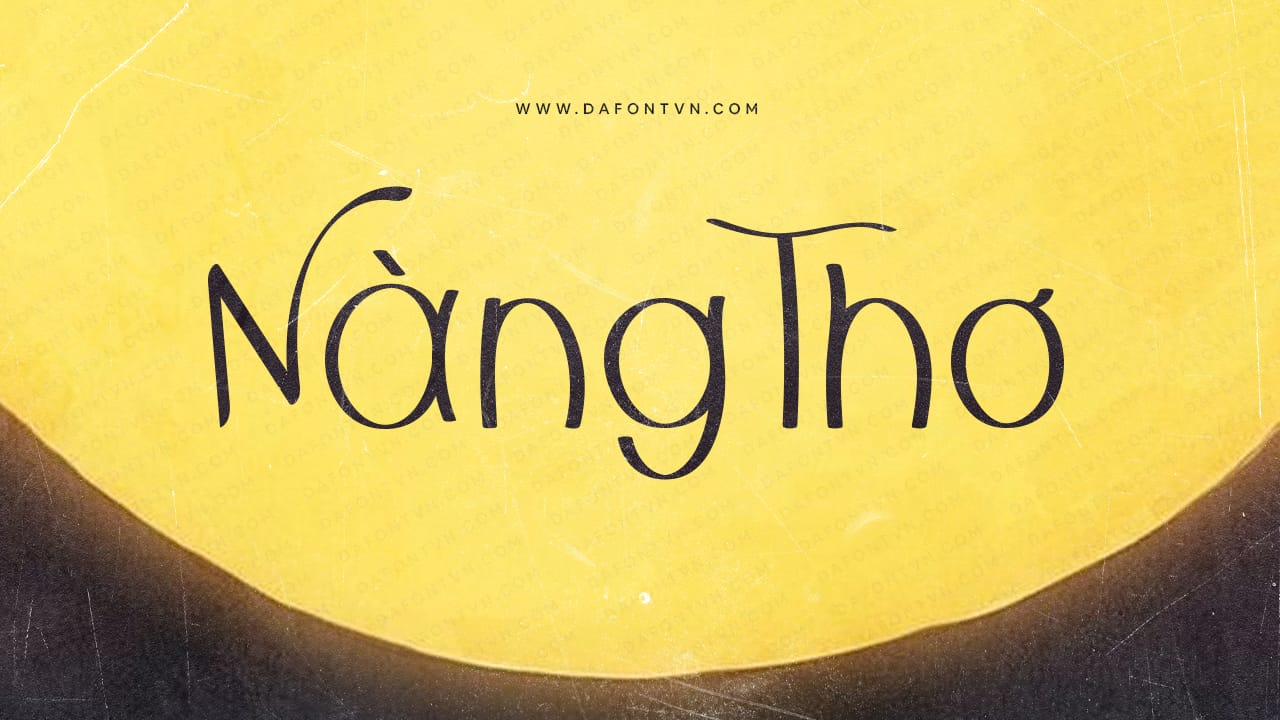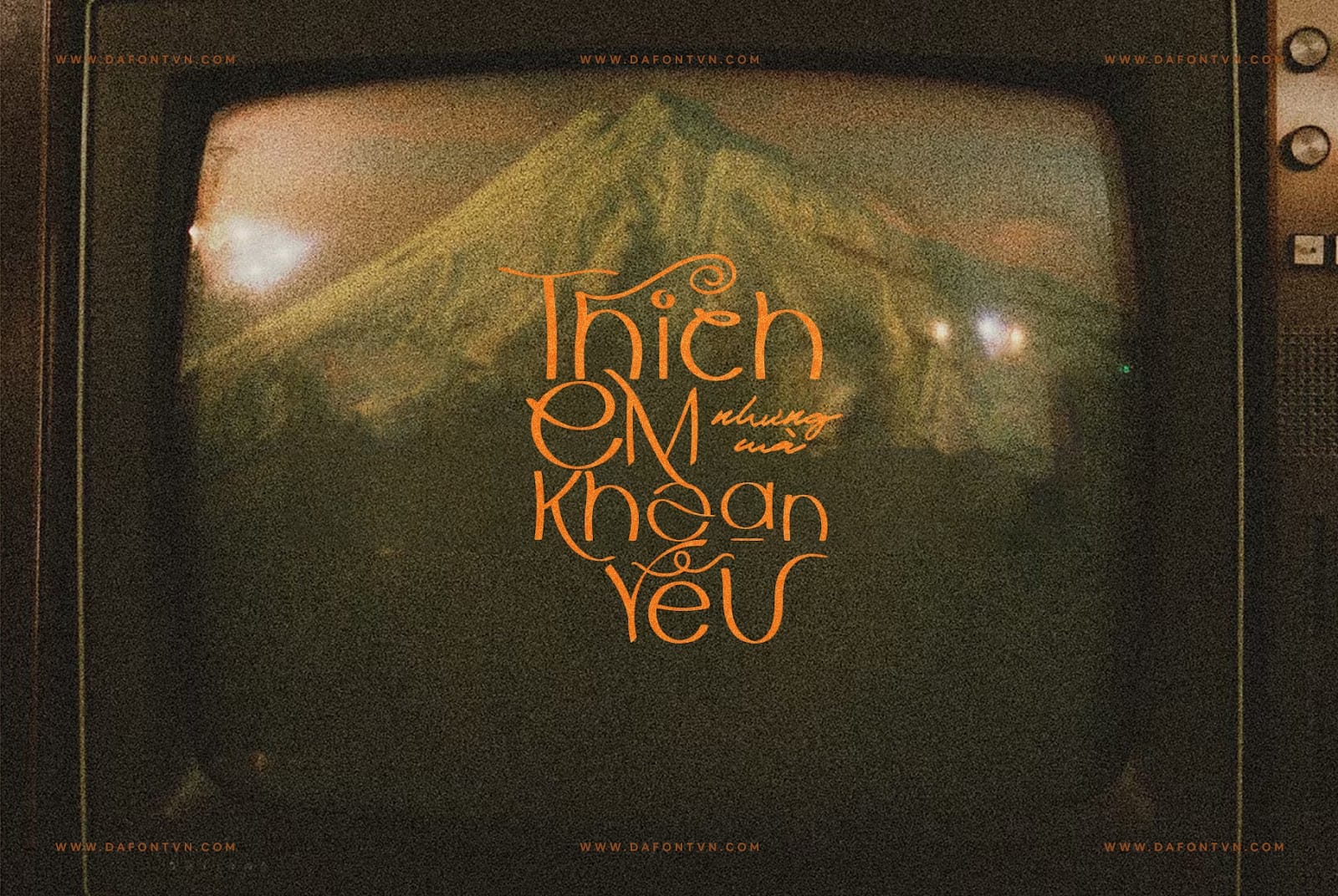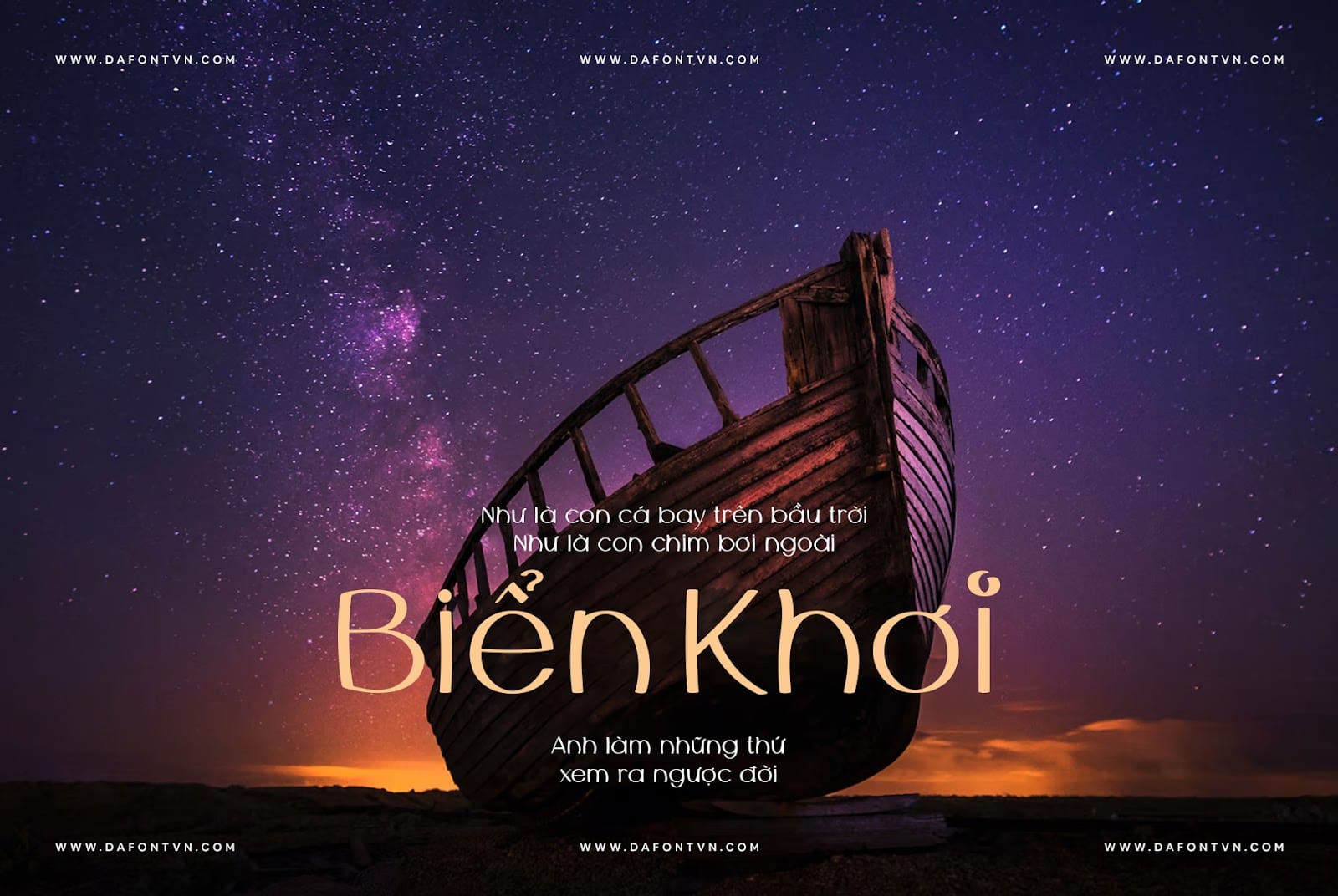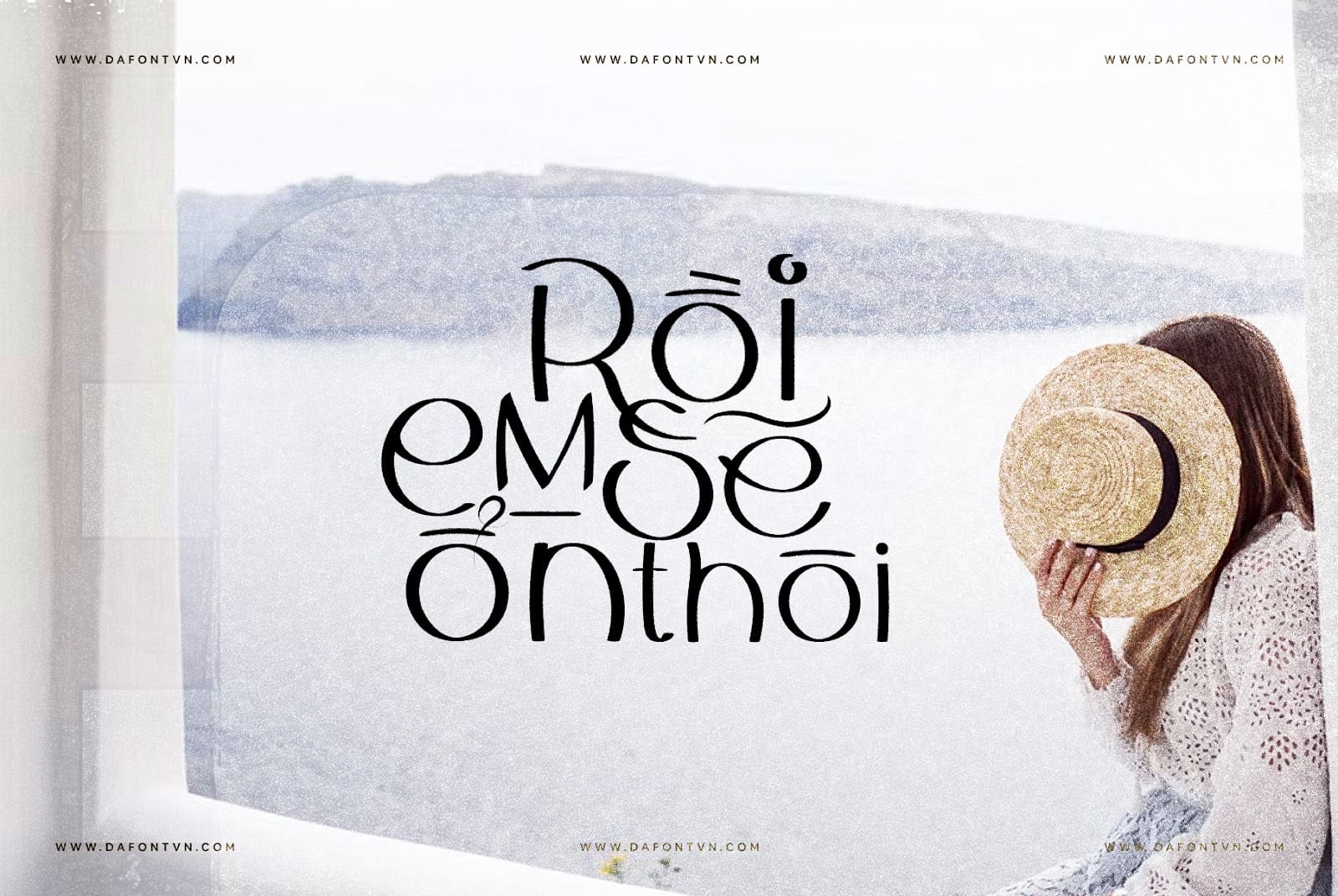
Font Việt hóa Fantasya – Hand Drawn Font
Fantasya là một font hiển thị vui nhộn hoàn hảo để tạo tiêu đề cho sách, tạp chí, trò chơi, phim hoặc bất kỳ loại thiết kế nào khác! Mỗi chữ cái viết hoa có ít nhất 3 lựa chọn thay thế khác để lựa chọn và điều này cho phép tạo ra nhiều tổ hợp chữ cái với nhiều thiết kế khác nhau.Bạn có thể sử dụng các ký tự thay thế trong Illustrator hoặc Photoshop bằng Glyphs. Font sẽ hoạt động với bất kỳ phần mềm nào nhưng một số không cho phép sử dụng các chữ thay thế và chữ ghép. Xin lưu ý rằng chỉ Photoshop CC mới cho phép bạn sử dụng tất cả các chữ thay thế và chữ ghép có trong đó. Nếu sử dụng trong phần mềm không hỗ trợ ký tự tượng hình, các chữ cái thay thế sẽ không khả dụng để sử dụng, chỉ các chữ cái thông thường mới hoạt động.